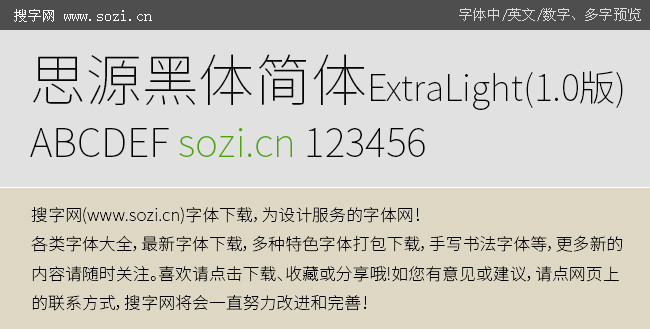
思源黑體簡體ExtraLight1.0
搜字網(wǎng)提供一款思源黑體簡體ExtraLight1.0中文字體下載,思源黑體是一款由谷歌聯(lián)合Adobe發(fā)布全新開源字體,是一款免費(fèi)、開源黑體字體。可共同呈現(xiàn)一致的視覺美感。本作品適用于書籍排版、報(bào)紙排版、畫冊設(shè)計(jì),網(wǎng)頁設(shè)計(jì)等應(yīng)用。